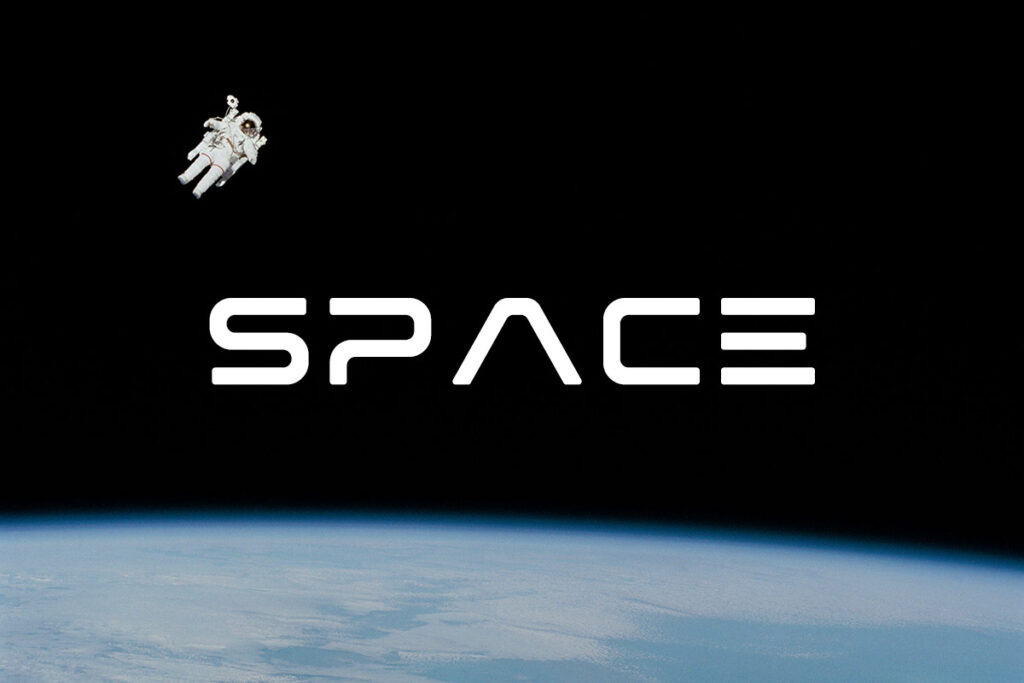
Trong kỷ nguyên số, ngôn ngữ thiết kế dần chuyển mình sang phong cách hiện đại, tinh gọn và mang hơi thở của tương lai. Việc sử dụng các bộ font chữ công nghệ Việt hóa giúp các bản thuyết minh dự án smart-home, văn phòng sáng tạo hay phối cảnh nhà lắp ghép trở nên chuyên nghiệp và đột phá hơn.
Đặc điểm nhận diện của dòng font chữ công nghệ Việt hóa hiện nay
Điểm lôi cuốn đặc trưng của phông chữ công nghệ nằm ở cấu trúc hình học chuẩn xác, các đường nét thường có độ dày đồng nhất hoặc mô phỏng các bảng mạch điện tử, lưới tọa độ. Thiết kế này tạo ra một diện mạo vững chãi, gợi liên tưởng đến sự chính xác của máy móc và các giải pháp xây dựng module hiện đại. Phiên bản font công nghệ Việt hóa đã được xử lý bảng mã Unicode kỹ lưỡng, giúp các dấu thanh không bị lệch khỏi khung chữ chính, duy trì sự ổn định thị giác cho toàn bộ văn bản.
Sức mạnh của dòng font này còn nằm ở khả năng hiển thị sắc sảo trên các thiết bị kỹ thuật số. Với độ mở ký tự lớn và khoảng cách được tính toán khoa học, các phông chữ này giúp người xem nhanh chóng nắm bắt thông tin về các giải pháp vật liệu mới hay công nghệ vận hành nhà container. Đây là phương án hiệu quả để định hình phong cách cho những dự án đề cao tính tiện nghi, sự tinh giản và khát vọng vươn tới không gian sống thông minh của tương lai.
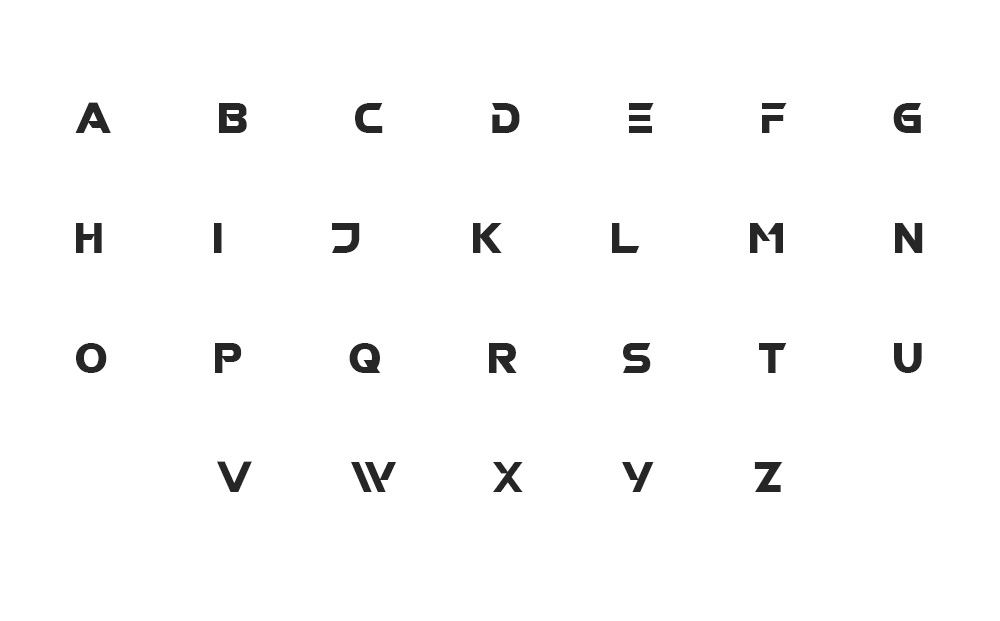
| Phân loại phong cách | Geometric Sans-serif / Futuristic / Sci-fi |
| Bảng mã hỗ trợ | Unicode chuẩn tiếng Việt |
| Các dòng tiêu biểu | Orbitron, Michroma, Exo 2, Quantico Việt hóa |
| Mục đích phù hợp | Giao diện app, poster công nghệ, decor văn phòng |
Gợi ý phối hợp: Phông chữ công nghệ thường có cá tính mạnh. Bạn nên sử dụng chúng cho các tiêu đề lớn hoặc các con số kỹ thuật quan trọng. Việc phối hợp cùng một phông chữ không chân tối giản cho phần nội dung thuyết minh sẽ giúp bản thiết kế đạt được sự cân bằng, tránh cảm giác quá khô cứng cho người đọc.
03 Ứng dụng phông chữ công nghệ vào thực tế xây dựng
Nhờ diện mạo hiện đại và giàu tính gợi hình, bộ phông chữ này mang lại giá trị thực tế cao trong quá trình quảng bá và hoàn thiện các công trình kiến trúc mới:
- Hệ thống bảng điều khiển Smart-home: Sử dụng font chữ công nghệ Việt hóa cho giao diện màn hình cảm ứng trong nhà lắp ghép giúp chủ đầu tư cảm nhận được sự hiện đại và đồng bộ với giải pháp thông minh của công trình.
- Hệ thống biển hiệu cho văn phòng Tech: Những nét chữ dứt khoát rất ăn ý khi gia công chữ nổi đèn LED tại các khu văn phòng container. Phông chữ này giúp không gian toát lên vẻ năng động, thu hút các doanh nghiệp khởi nghiệp và đổi mới sáng tạo.
- Trình bày hồ sơ kỹ thuật chuyên sâu: Với độ hiển thị rõ ràng, các phông chữ này giúp các thông số về kết cấu khung thép hay hiệu suất năng lượng của vật liệu panel trở nên nổi bật, tạo ấn tượng về sự chuyên nghiệp trong mắt khách hàng.
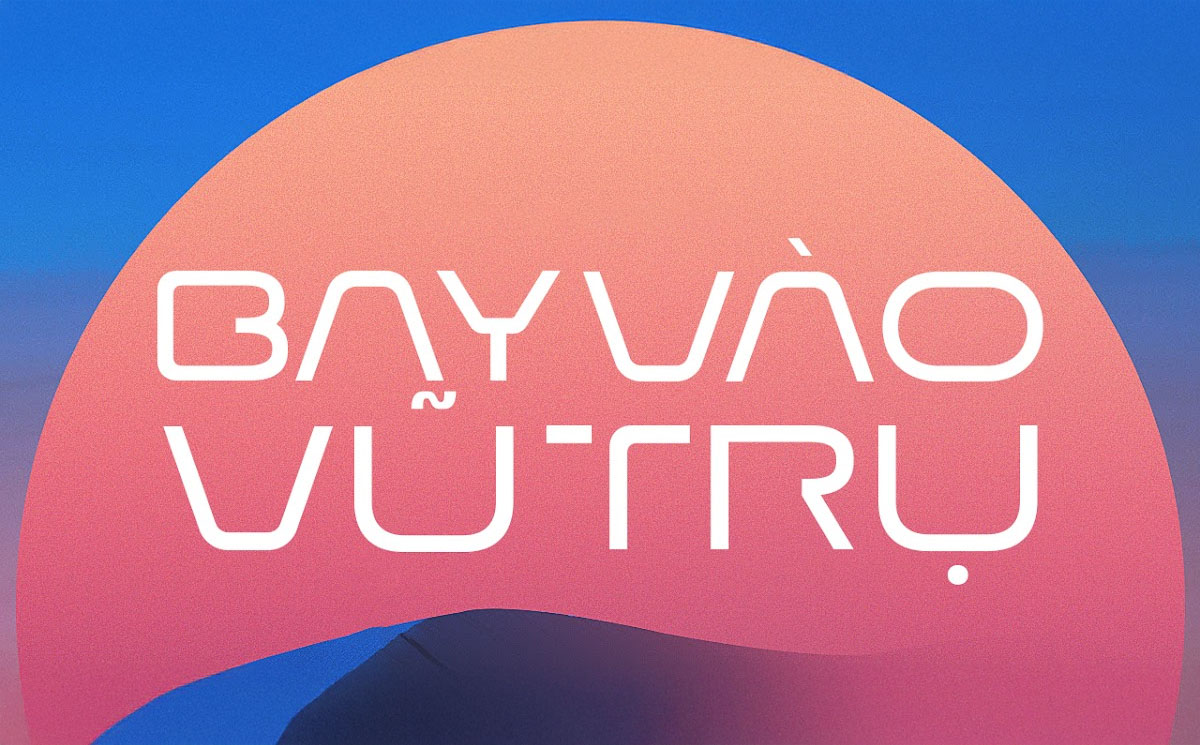
03 Lưu ý để bố cục font chữ công nghệ hài hòa và sắc nét
Để khai thác hiệu quả vẻ đẹp của dòng font đặc thù này mà không làm rối mắt người xem, người thiết kế nên lưu tâm một số lưu ý kỹ thuật sau:
- Chú trọng khoảng trắng: Phông chữ công nghệ cần không gian xung quanh đủ rộng để các nét chữ hình học được tỏa sáng. Việc trình bày quá dày đặc sẽ làm mất đi tính thanh lịch và hiện đại của bộ chữ.
- Lựa chọn màu sắc mang tính “Digital”: Phong cách này phát huy hiệu quả thị giác cao khi phối cùng các tông màu lạnh như xanh neon, trắng bạc, đen chì hoặc cam điện tử. Tránh các màu sắc quá trầm mặc hay hoài cổ.
- Kiểm soát khả năng đọc: Một số font Sci-fi có cấu trúc ký tự khá lạ mắt. Bạn chỉ nên dùng chúng cho các cụm từ ngắn. Đối với các đoạn văn bản hướng dẫn dài, hãy trung thành với các biến thể đơn giản hơn trong gia đình font đó để người đọc không bị mỏi mắt.